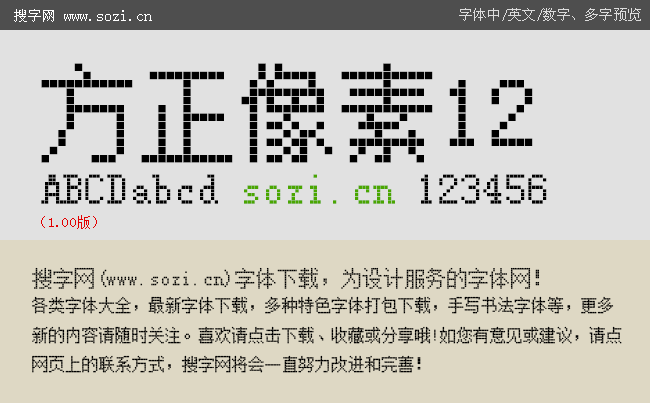
方正像素12
搜字網(wǎng)提供一款方正像素12中文字體下載,方正像素字體由正方形像素點組成的基于黑體、宋體基本字形的一套字體系列。方正像素體具有規(guī)范、工整,容易辨認的特點,適用于LED屏等電子屏幕,在易識的同時,體現(xiàn)科技感和現(xiàn)代感。適合書籍設計、展板設計、海報設計等廣告設計場合使用。